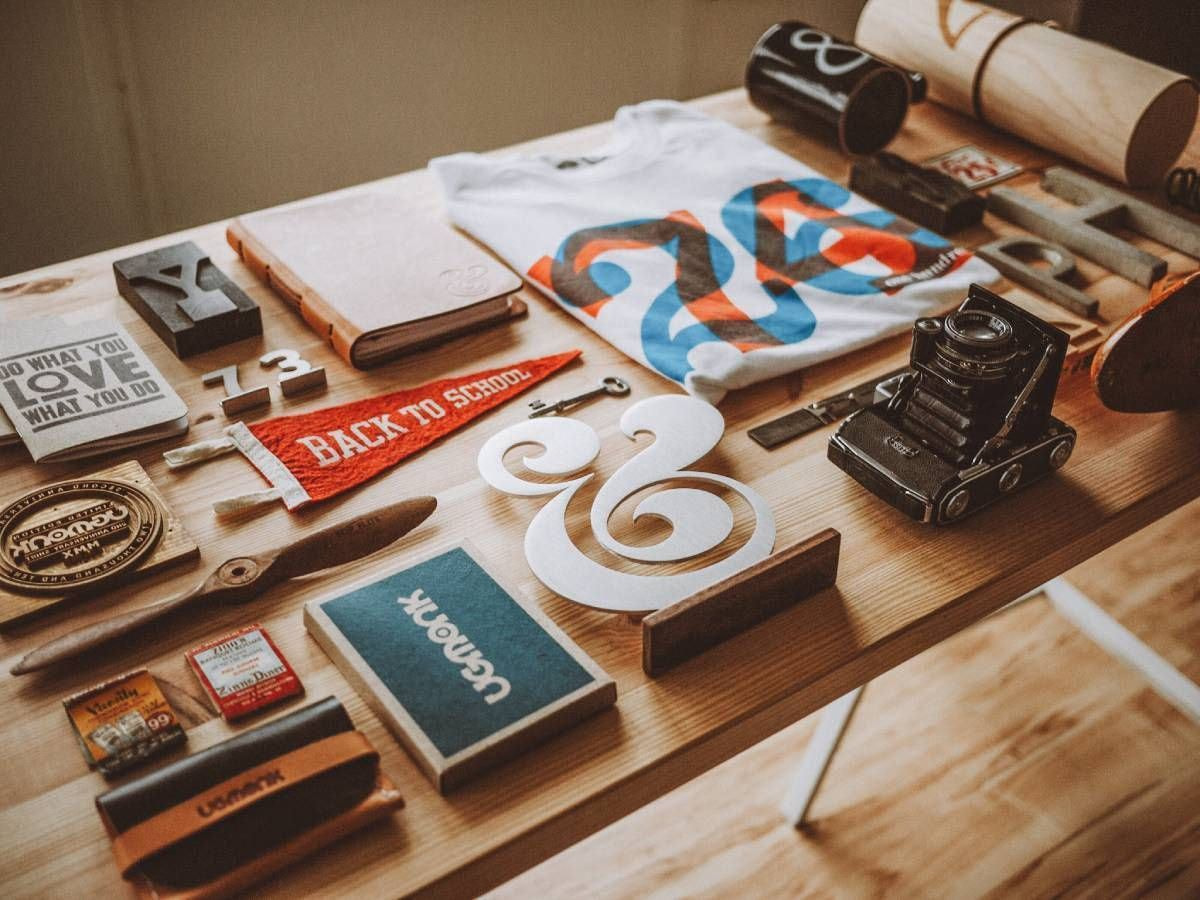
文字を目にした際、その文字の雰囲気やスタイルによって受け取る側の印象は大きく変わります。手書きの文字を見て、その人の人となりを感じ取れるように、デジタルの文字も使うフォントや書体によって与えるイメージは様々です。
デザインにおいても同様で、デザインに文字が含まれている場合、その文字が与えるイメージが商品の印象を左右します。そのため、テキスト入りのデザインを衣服にプリント・刺繍を追加する際、またはロゴを作成する際は、正しくフォント選びを行うことが大切です。
今回は、思い通りのデザインを完成させるための、初心者でもわかるフォント選びのコツをご紹介。テキストを含むデザインを行う際に知っておくこと、ブランドに合ったフォントの選び方や組み合わせ方のコツについて解説します。
書体とフォント
パソコン上で文字を書く際、フォントや書体を選ぶことになります。フォントと書体はコンピュータ上で書く文字として同じものと考えている方が多いですが、厳密には異なります。
大まかに言うと、書体は文字のスタイルを指します。例えば、「楷書体」、「明朝体」、「ゴシック体」などの、同じスタイルを持つグループによって分かれます。
一方フォントは、各書体においてサイズごとに作られた文字(大文字、小文字、数字、記号)のセットを指します。フォントは元々は、活字版印刷で使用された金属板から由来しています。
代表的な書体
日本語フォント
日本語フォントの書体は大きく4つに分かれ、「明朝体」、「ゴシック体」、「筆書体」、「デザイン書体」があります。これらは、それぞれ与えるイメージや代表的な用途が異なります。以下でそれぞれの特徴を見ていきましょう。
明朝体
明朝体は最も代表的な日本語フォントの1つです。この書体は横線が細く、縦線が太い特徴があります。曲がり肩の右側に三角形の「うろこ」と呼ばれる山があり、毛筆のタッチが取り入れられています。
この書体は、落ち着き、真面目、上品、フォーマル、女性的と言う印象を与えます。新聞や論文など、「読む文章」で多く使用されるのがこの書体です。
ゴシック体
ゴシック体は明朝体と並んで代表的なフォントです。明朝体とは対照的に、縦、横の太さが同一という特徴があります。
この書体が与える印象はモダン、カジュアル、楽しい、親しみやすさ、男性的などがあります。「読ませる」というよりも「見せる」という、視覚に訴える書体で、パッと目に入りやすく、ポスターやプレゼンなどによく使われます。
ゴシック体の派生
丸ゴシック体
ゴシック体を丸くアレンジしたのが丸ゴシック体です。ゴシック体と同様、縦横の太さは均等ですが、画の先端や角が丸くなっています。
この書体はやさしい、ソフト、面白さ、などの印象を与えます。ポップなデザインに使われることが多いですが、標識など、堅い内容や注意事項にあえて使うことで、ソフトに伝えられる効果があります。
ゴシックと明朝の中間のフォント
ゴシック体と明朝体の中間のようなフォントもあります。これらのフォントは縦線と横線の太さが異なる点が明朝体と似ていますが、ウロコと呼ばれる線の端の山がありません。「タイポス」や「フォーク」、「スキップ」(と呼ばれるフォントがこの一例です。
筆文字
明朝体よりもさらに毛筆のタッチの強い書体で、行書体、教科書体、楷書体などがこのグループに入ります。筆で書いたような「和風」のイメージを出し、古典的、伝統的な印象を与えることができます。
デザイン書体
上記のどのカテゴリーにも入らない、個性的な書体がデザイン書体です。フリーハンドの手書き風の文字や、ラインに装飾がついている文字など、さまざまなフォントが存在します。遊び心や面白さ、個性、おしゃれ感を表現したい時に使われます。
英語フォント
次に、アパレルや小物などのデザインでもよく使われる英語フォントについて見ていきましょう。
Serif(セリフ)
セリフは、日本語書体の「明朝体」に当たり、横線が細く、縦線が太く、線の端にウロコと呼ばれる山がついています。英文でも書物や論文で使われ、フォーマル、真面目、落ち着きというイメージを与えます。
フォント例:Times、Garamond、Georgia
Sans Serif(サン・セリフ)
サン・セリフは、日本語の「ゴシック体」に当たる書体で、縦横の線の幅が均等です。モダン、カジュアル、楽しいというイメージを与え、視覚に訴えるポスターやデザインなどで使われます。
フォント例:Arial、Helvetica、Verdana
Script(スクリプト書体)
スクリプト体は、筆記体のような書体で、手書き風の個性的なイメージを与えます。
フォント例:Brush Script、Pacifico、Allura、Zapfinoなど
スクリプト書体の中にも「フォーマル」と「カジュアル」に分類され、「フォーマル」は斜体で流れるような書体で「空想的」、「繁栄」というイメージがあります。
一方で「カジュアル」は、斜体の度合いが少なくより読みやすく、「現実的」、「ポップ」な印象を与えます。
Decorative(デザイン書体)
デザイン書体は、手書き風書体など個性的な見た目の書体です。他とは異なるオリジナル感を出したい場合にぴったりで、デザインの中でテキストを際立たせます。デザイン書体はさまざまな種類があるので、ブランドに合ったものを見つけましょう。
Monospace(等幅書体)
英語フォントには、全ての文字の幅が等しいMonospace(等幅)書体と、文字によって幅の異なるPropotional(プロポーショナル)書体が存在します。
等幅書体はタイプライターで使われていた書体で、脚本などに現在も使われます。長い文章ではプロポーショナル書体の方が読みやすいですが、デザインでは等幅書体を使うことで、真面目、書物のような、タイプライターで書いたような印象を与えられます。
数字フォント
言語を問わず万国共通の数字はフォントやデザインによって大きく印象が変わります。数字フォントの特徴は以下のものがあります。
数字の縦幅
数字フォントには、「ライニング数字」と呼ばれる、数字の上下のラインとが揃っているものがあります。反対に、上下にはみ出している数字は、「オールドスタイル数字」と言います。見やすさで言えば、ライニング数字を選ぶべきですが、個性的なデザインをしたい場合はオールドスタイルもありでしょう。
数字の横幅
英語フォントでもご紹介したように、数字にも等幅ライニングのフォントのように横幅が均一のフォントと、数字によって幅の異なるプロポーショナル数字があります。
数字フォントの比較方法としては、$123,456,789,00%¥を入力してそれぞれのフォントに変換して比較してみるとわかりやすいでしょう。
フォントを使ってデザインする
デザインを行う上で使用するソフトウェアにはさまざまな種類のものがありますが、テキストベースのデザインを行う際は、Adobe illustrator のようなベクタ形式のものが適しています。Adobeにはすでに豊富なフォントが内蔵されています。
ブランドのスタイルに合わせる
文字を使ったデザインを開始する前に、まずはご自身のブランドに合ったフォントを選びましょう。フォントが与える印象がブランドのものと一致していると、ショップブランドの統一したイメージを作ることができ、顧客に覚えてもらいやすくなります。
反対にブランドイメージと合わないフォントを選んでデザインをしてしまうと、商品とブランドイメージの間にギャップが生じ、顧客が認識しづらくなってしまうので気をつけましょう。
デザインに使うメッセージが決まったら、デザインしっくりくるフォントと出会うため、さまざまなフォントを試して熟考することをお勧めします。
フォントの組み合わせ
複数のフォントを組み合わせてデザインを作成する場合、組み合わせ方によって出来上がりが異なってきます。
以下に、フォントを組み合わせる際のポイントをいくつかご紹介します。
同じ書体ファミリーを使う
同じ書体ファミリーを使うことで、簡単にバランスの取れた組み合わせを作ることができます。フォントの太さ、サイズ、英語フォントなら大文字・小文字を切り替えることでアクセントをつけることができます。
縦の大きさを揃える
大きさが類似している、また小文字の高さ (x-height と呼ばれています) が同じである書体は相性が良いとされています。異なる書体を使った場合でも、文字の大きさを揃えることでバランスがとれ、かつ個性的な雰囲気を追加することが可能です。
フォントを微調整
ソフトウェアでフォントを決定したら、あとは文字間を調整したり、左揃え、右揃えなど文字の揃え方を調整してフィットする形を探しましょう。また文字間を調整することで、フォントだけでは出せない個性的な印象を加えることもできます。
ただ、フォント自体の縦幅や横幅を変えることは、フォント本来のスタイルを変えてしまうことになるのでお勧めできません。より幅を狭めたい場合は、文字間や文字の大きさを変更するか、別のフォントを使うことを考えましょう。
まとめ
フォントの種類は日々増え続け、トレンドも変わっていきます。文字もデザインの良し悪しを決める重要な要素、ポイントや注意点に気をつけて、ブランドイメージにピッタリ合うものを見つけましょう。